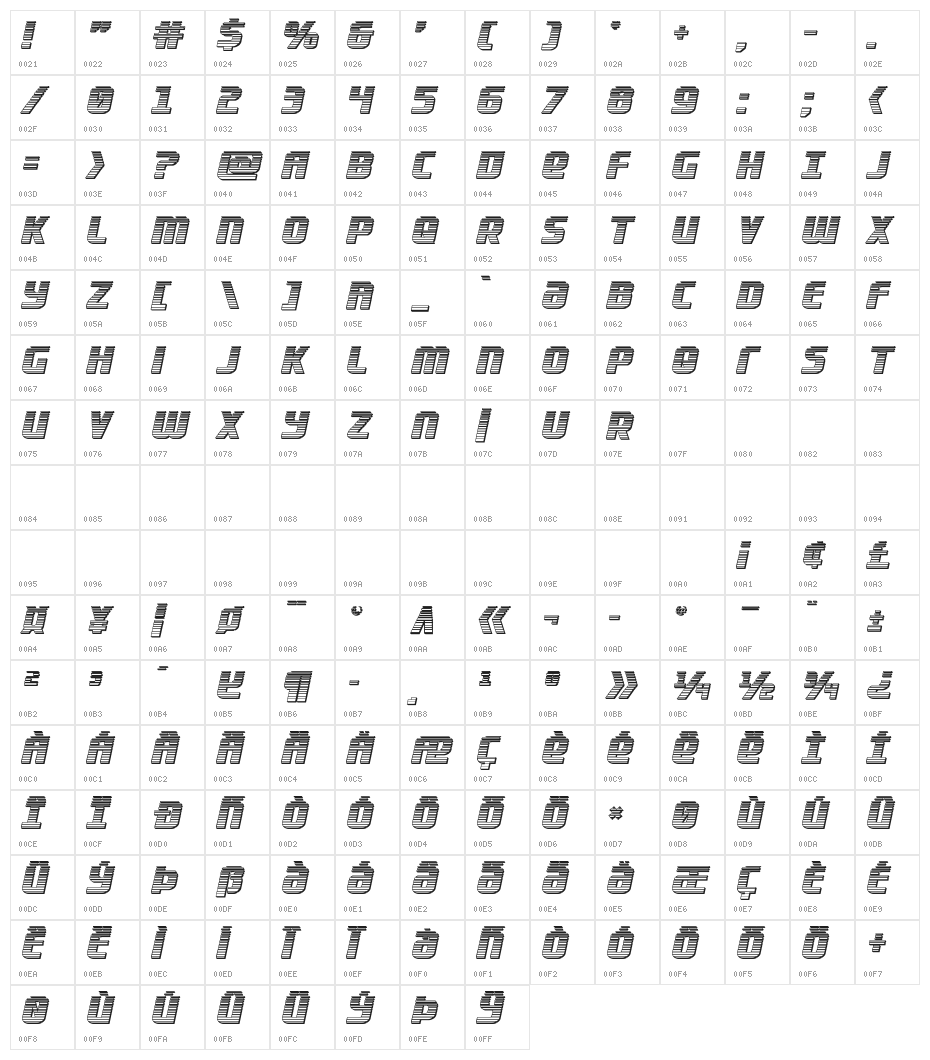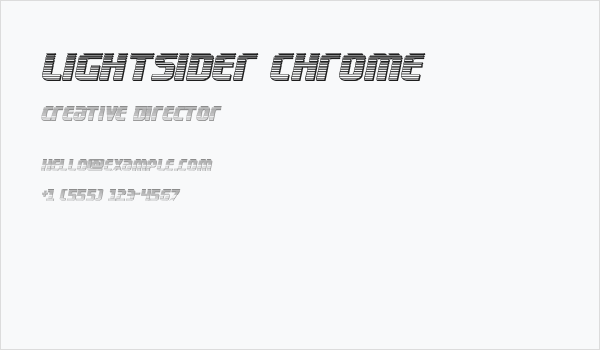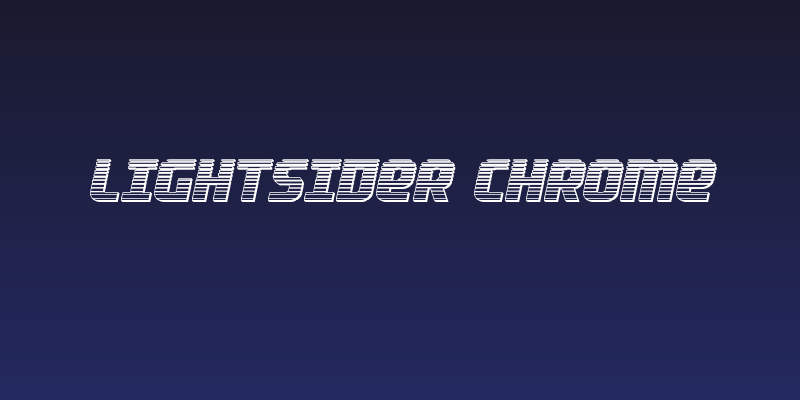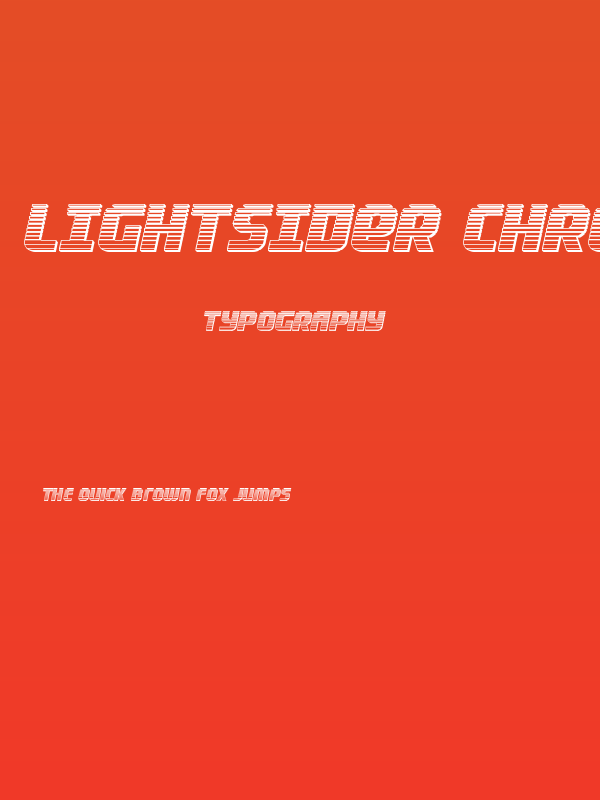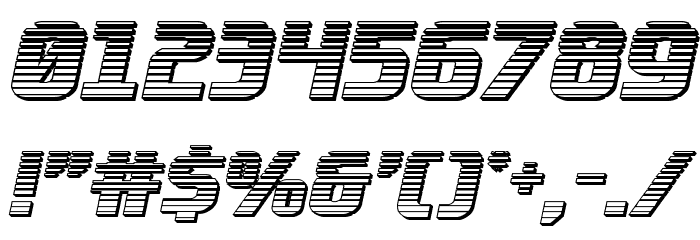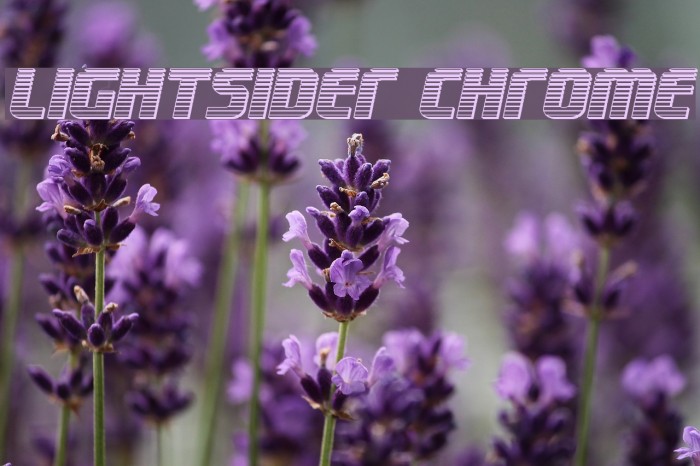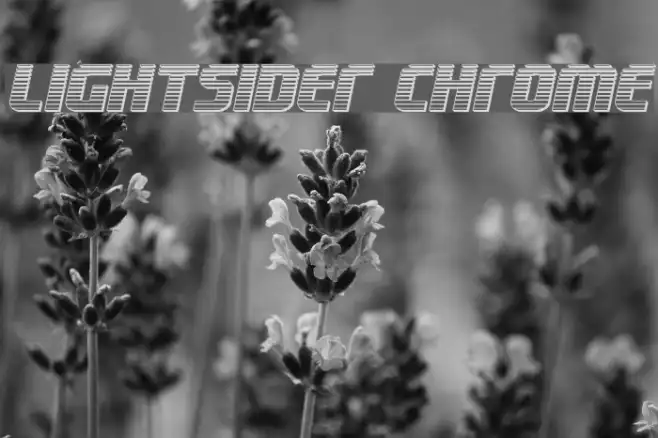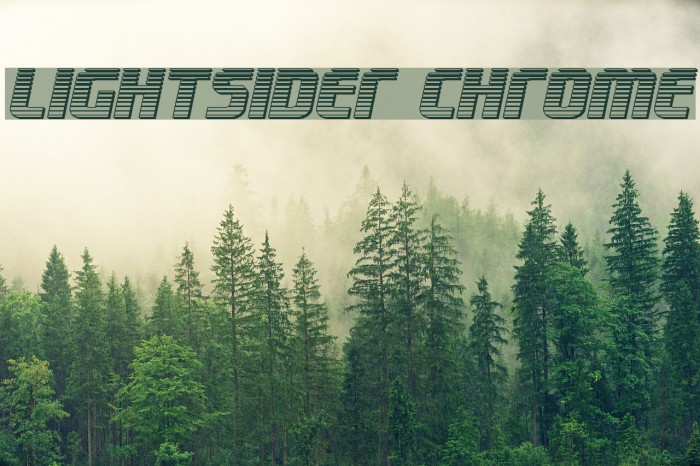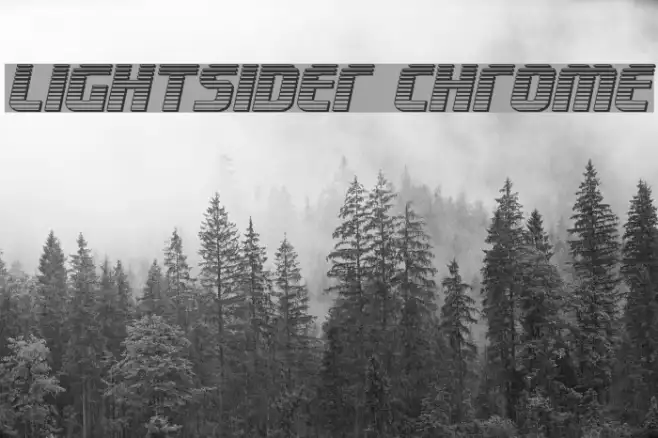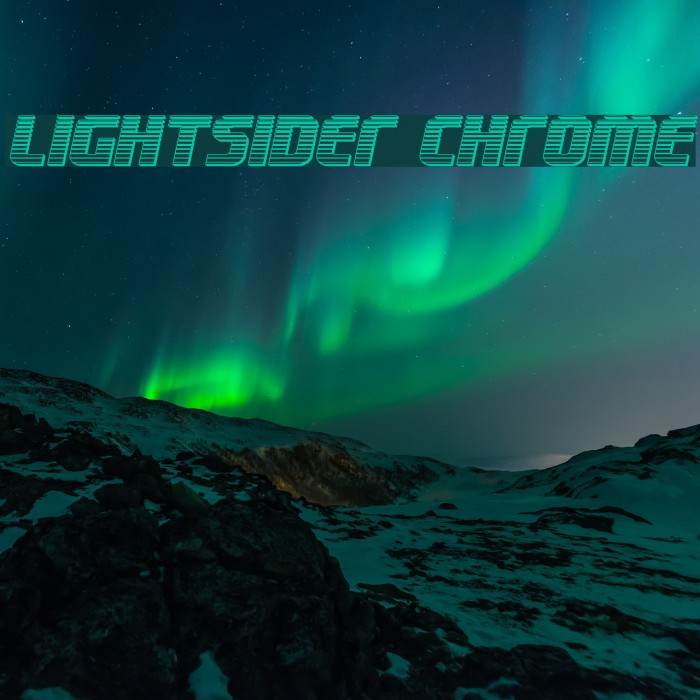
Lightsider Chrome Font
| Kategorien | Retro |
| Gesamtstil | Futuristic, Retro |
| Anwendungsfall | Headlines, Posters, Branding |
| Vorgeschlagene Projekte | Ideal for retro-futuristic designs, sci-fi themed projects, eye-catching posters, and branding materials. |